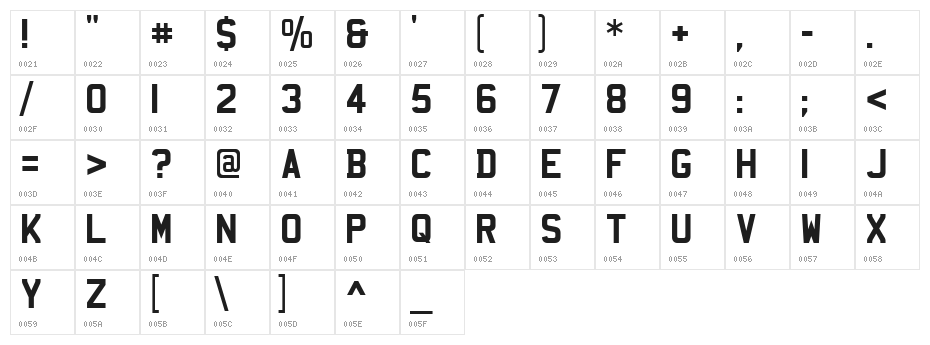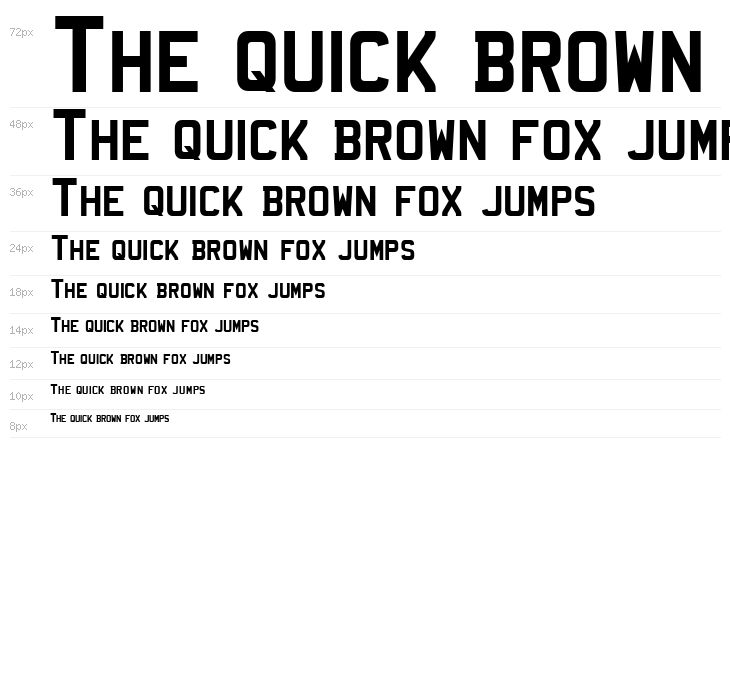
Mandatory Font
| Caz de utilizare | Headlines, Logos, Signage |
| Proiecte propuse | Ideal for branding, signage, and headlines where a strong, impactful presence is needed. |